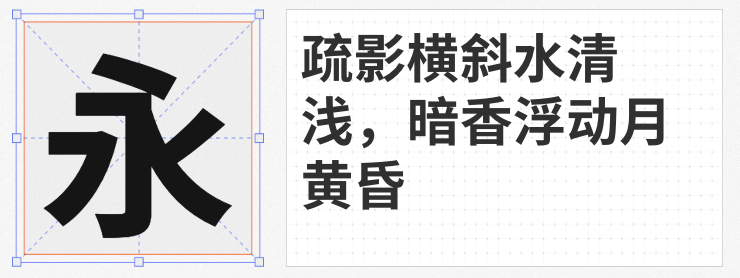
在海报设计中,字体不仅是信息传递的载体,更是视觉风格的核心。选择一款兼具美感与实用性的免费商用字体,既能降低设计成本,又能提升作品质感。本文推荐四款适合海报设计的免费商用字体,涵盖现代、力量、创意等多种风格,助力设计师轻松打造吸睛视觉。
1. 思源黑体 SC Bold
作为Adobe与Google联合开发的开源字体,思源黑体支持中、日、韩、繁体中文,2.2版本更推出可变字重功能,可在软件中无级调节粗细,满足标题、正文等多场景需求。其笔画简洁有力,字形端正,适合科技、商务类海报,尤其适合需要多语言排版的设计。免费商用的属性,使其成为企业宣传的“安全牌”。
2. 阿里巴巴普惠体 3 65 Medium
专为电商场景设计的阿里巴巴普惠体,以“少年感”为核心理念,字形瘦长、重心上提,笔画简化(如标题字省略出脚),整体风格轻盈灵动。适合快消品、时尚活动等需要传递年轻活力的海报设计,既能保证远距离识别,又能通过简洁的笔画提升版面呼吸感。
3. 阿里妈妈数黑体
数黑体以“图形感”与“书写感”的平衡为特色,字形饱满、布白现代,落笔厚实却简练,特殊笔画处理(如断笔、弧度优化)赋予其醒目、时尚的气质。适合潮流品牌、音乐节、科技发布会等场景,能快速吸引观众注意力,同时保持文字的可读性。
4. 鼎猎诺言体
以宋体为基底,鼎猎诺言体融入棱角分明的笔画设计,既有“一诺千金”的稳健感,又带自主创新的锐气。适用于美食、文化展览、美妆护肤等行业的海报,尤其能传递传统与现代融合的视觉语言,为封面、标题增添文化厚重感。